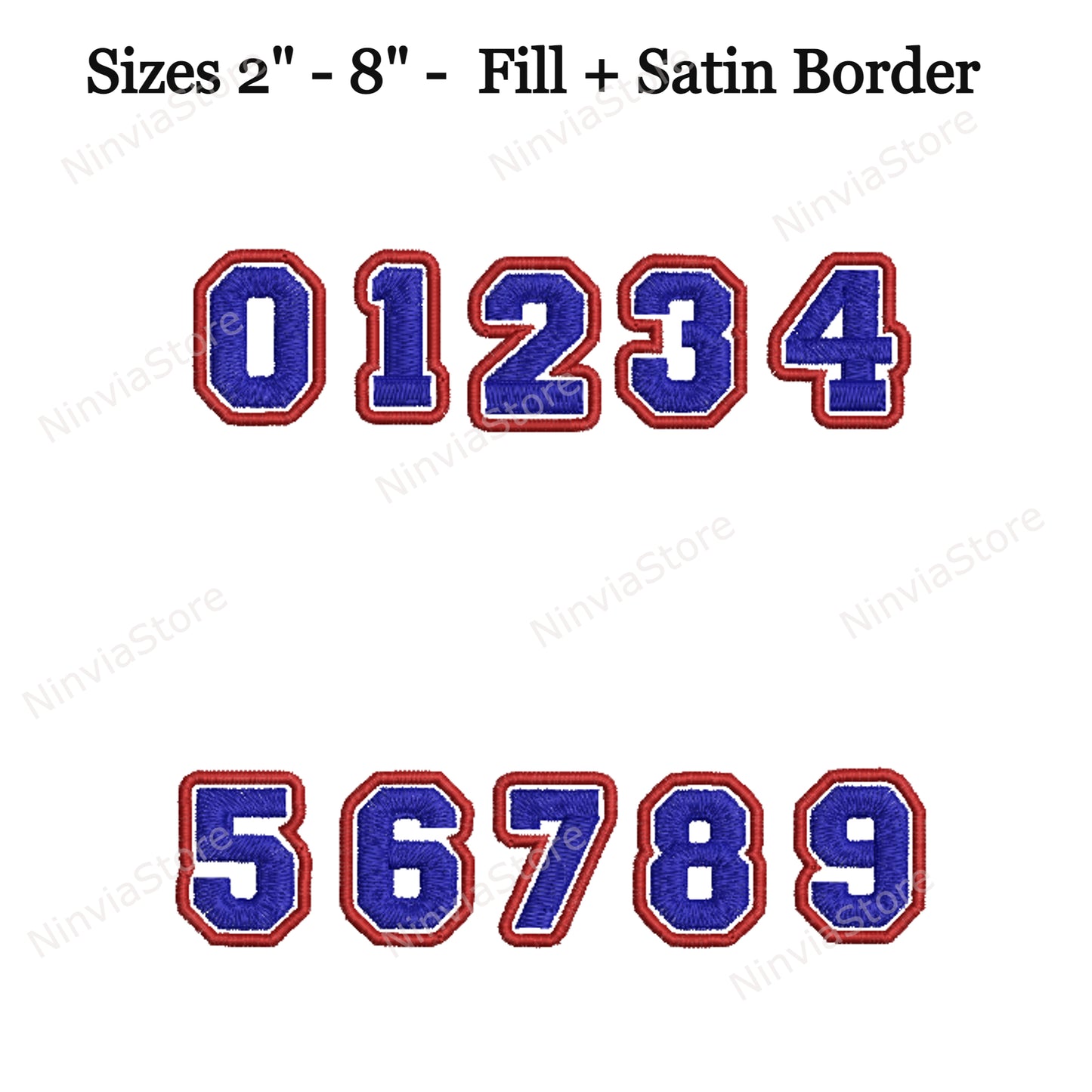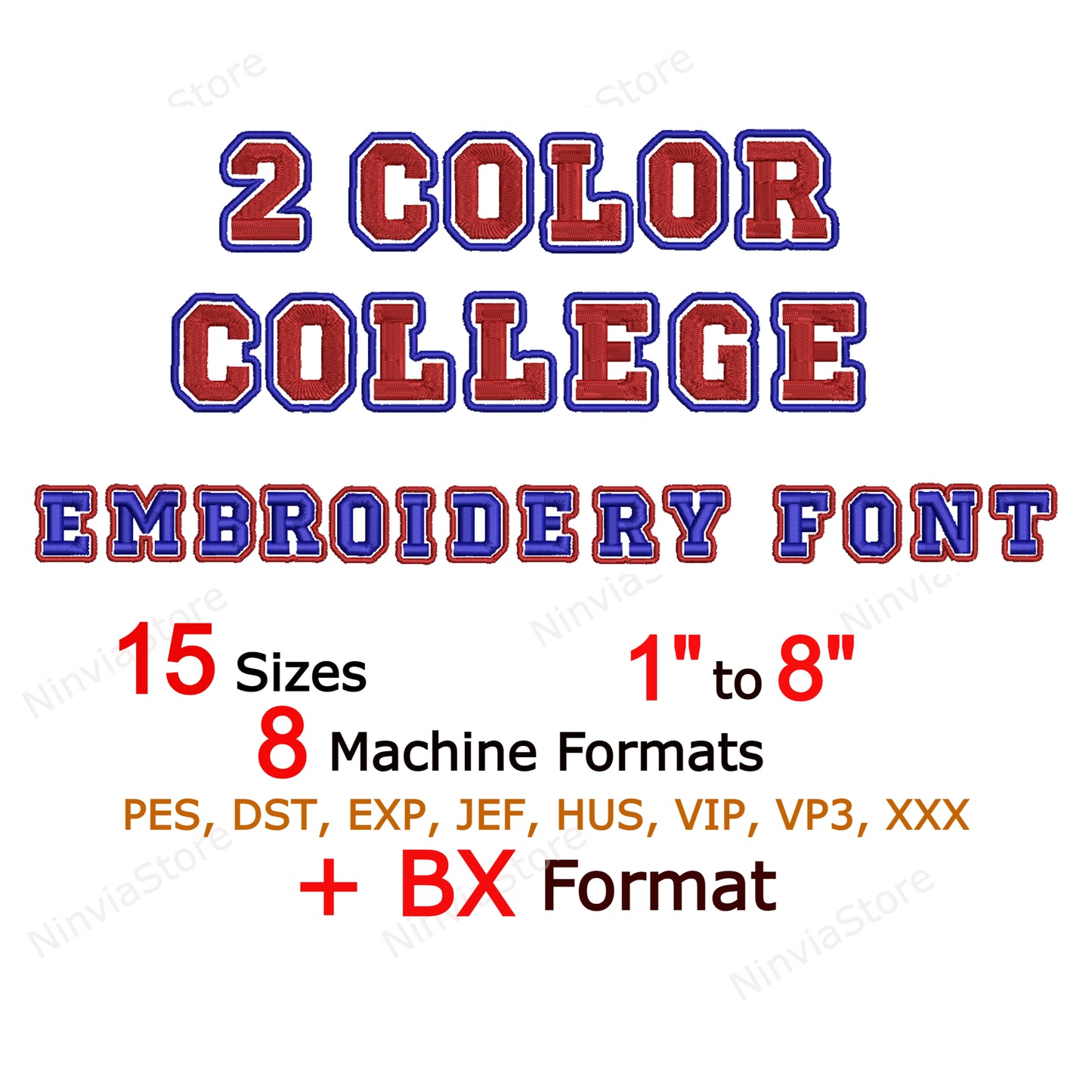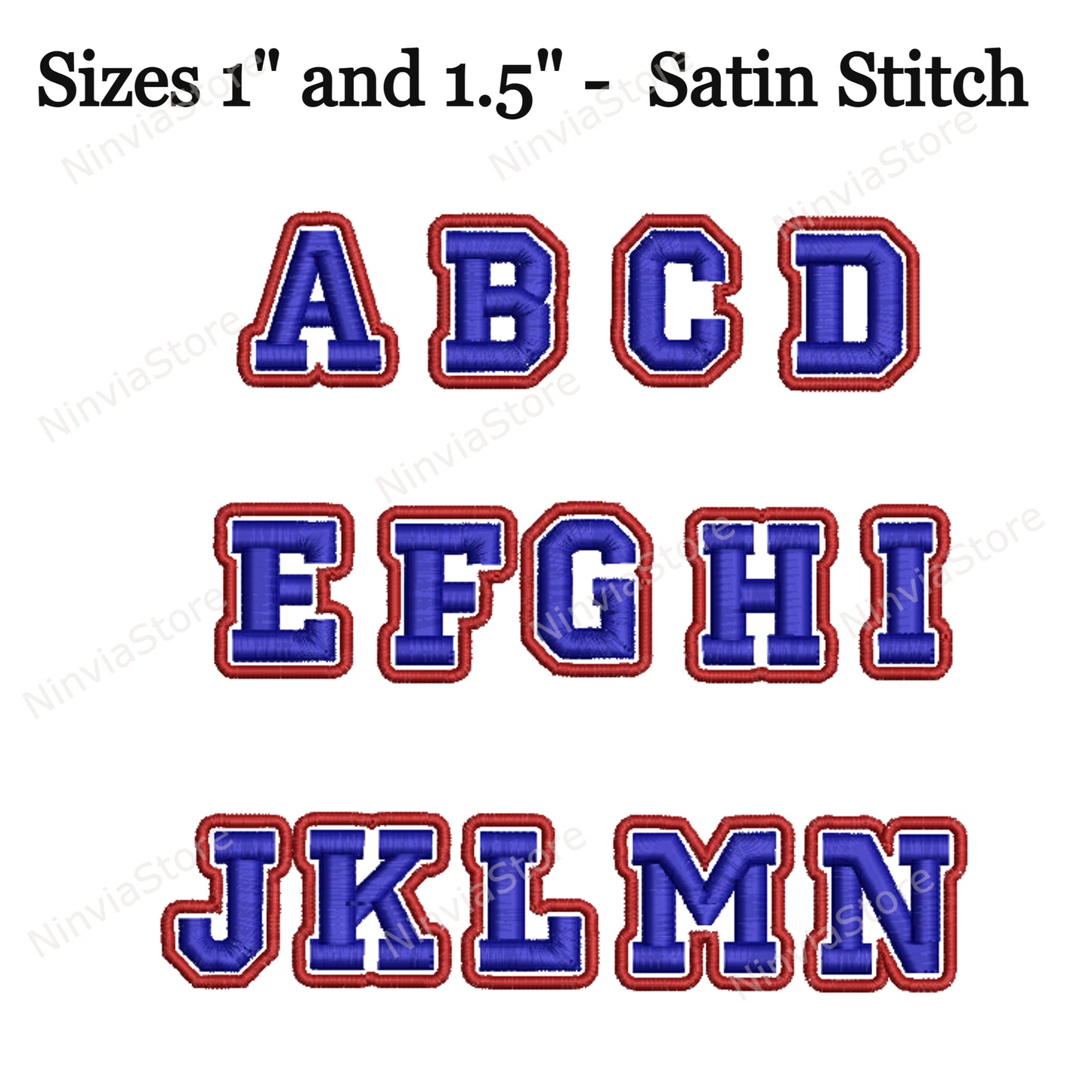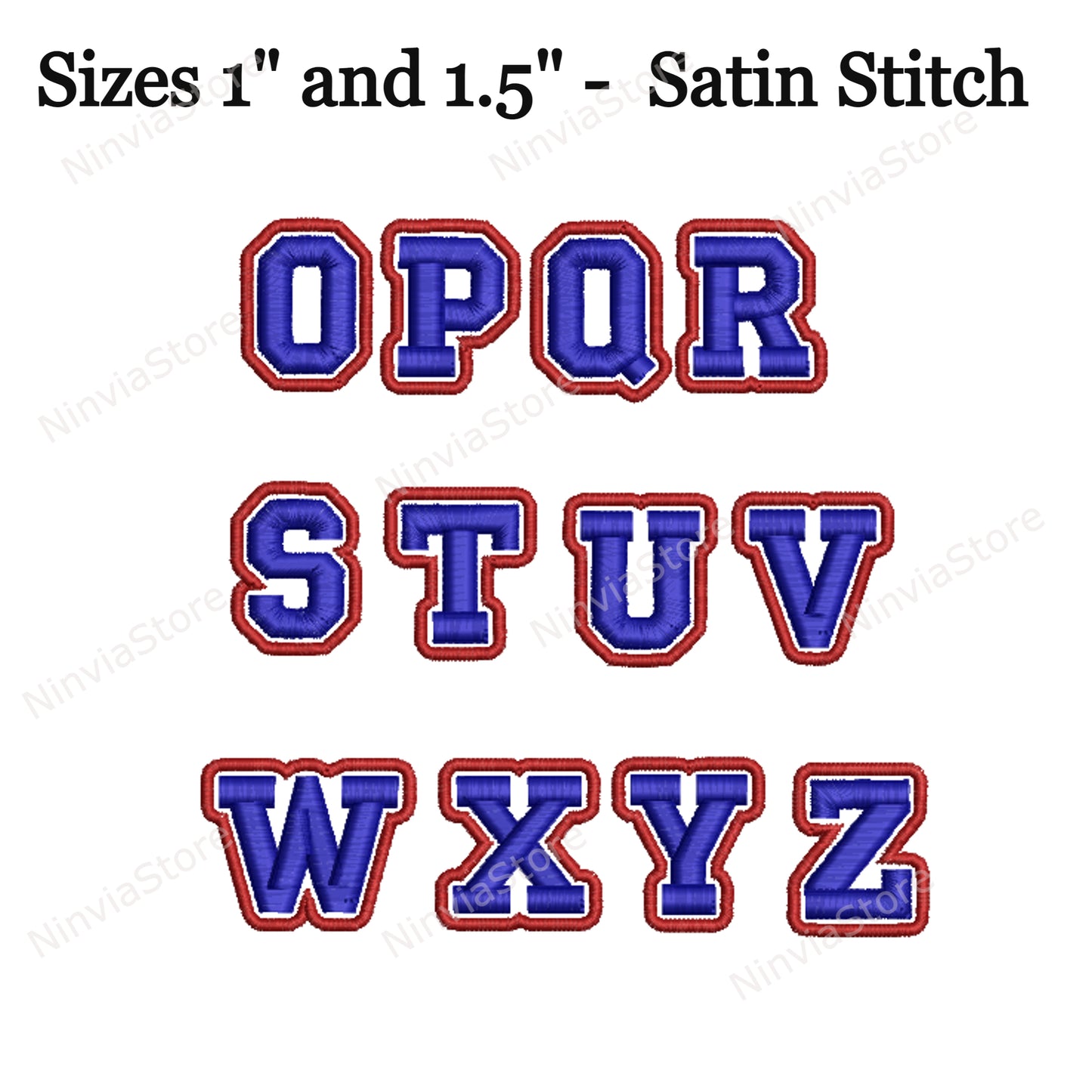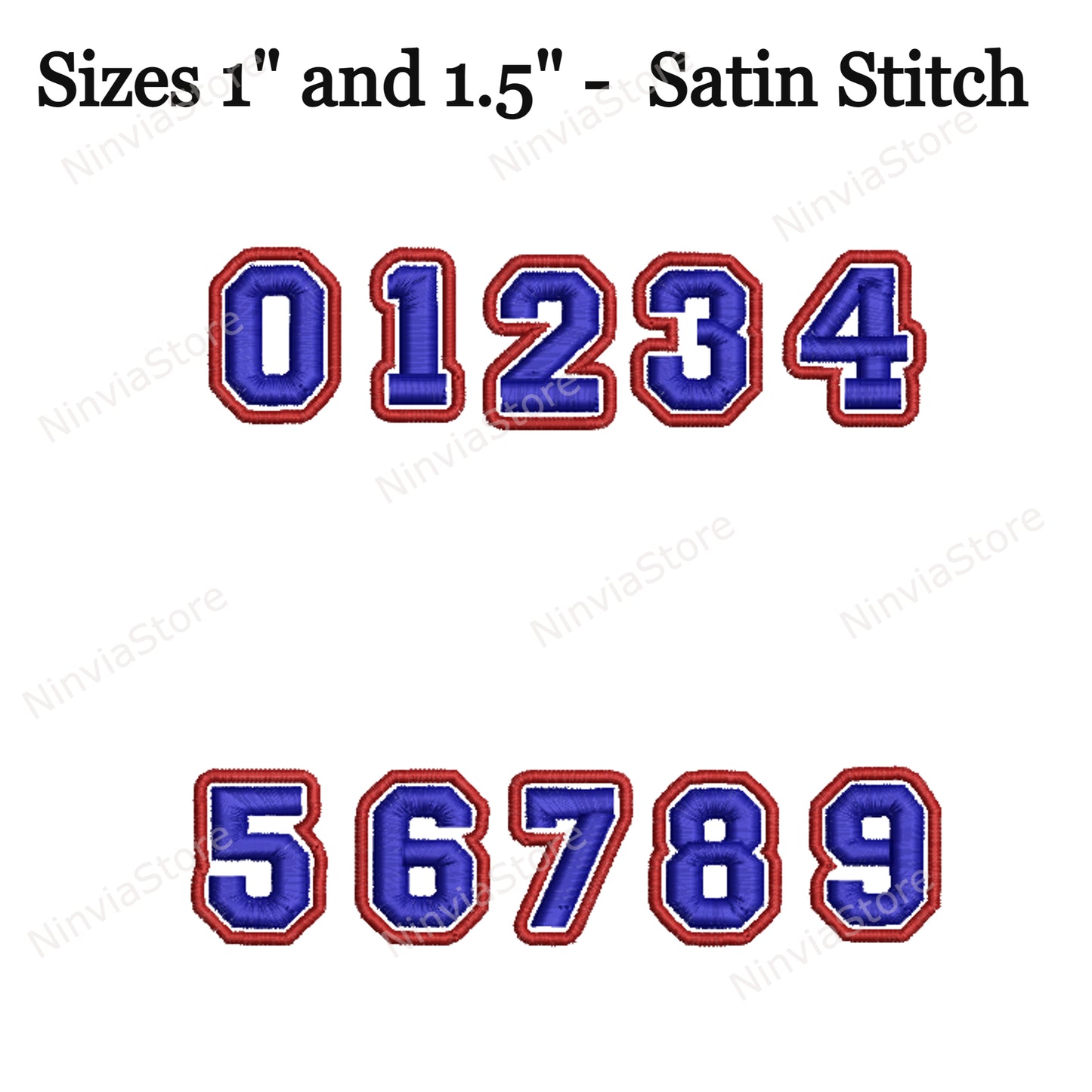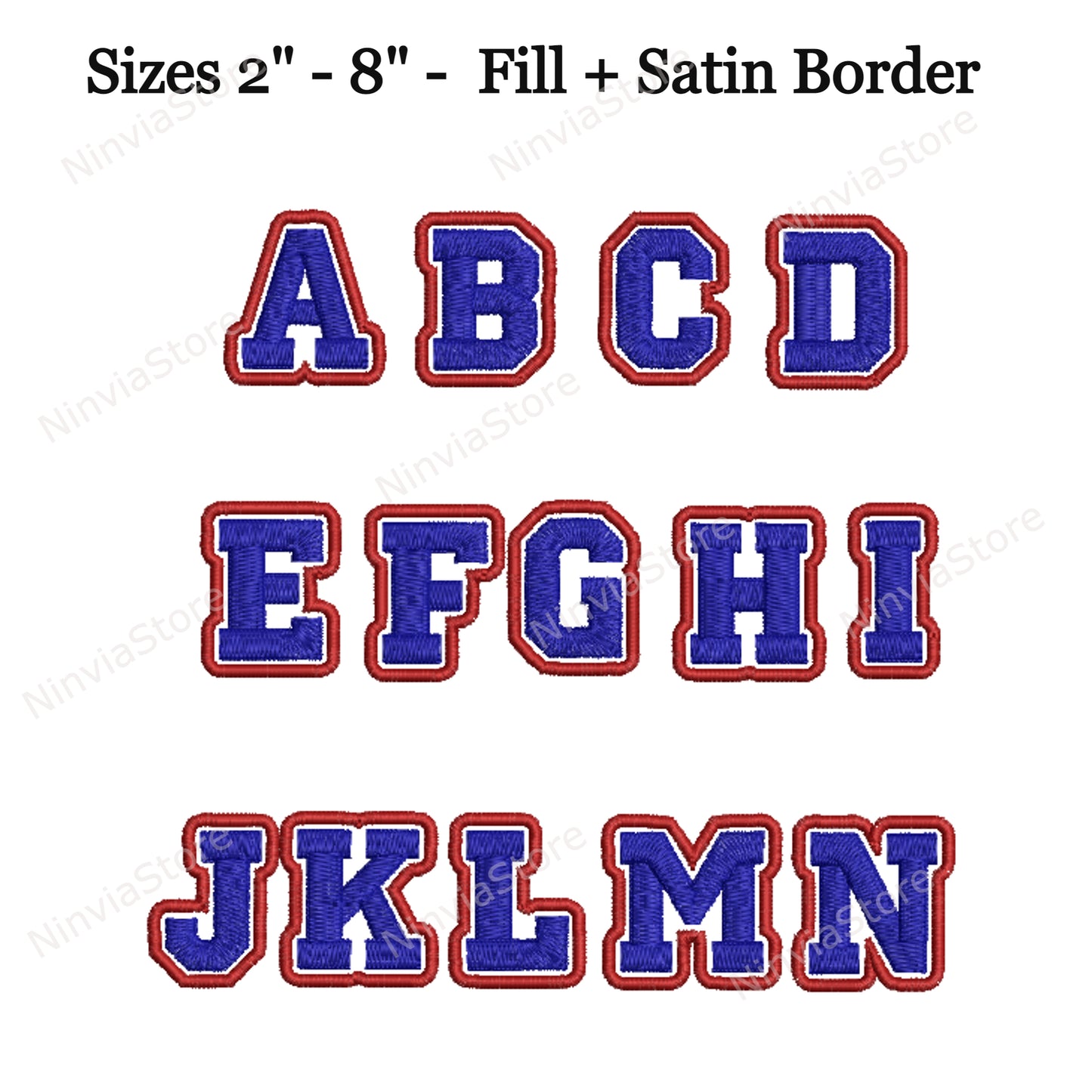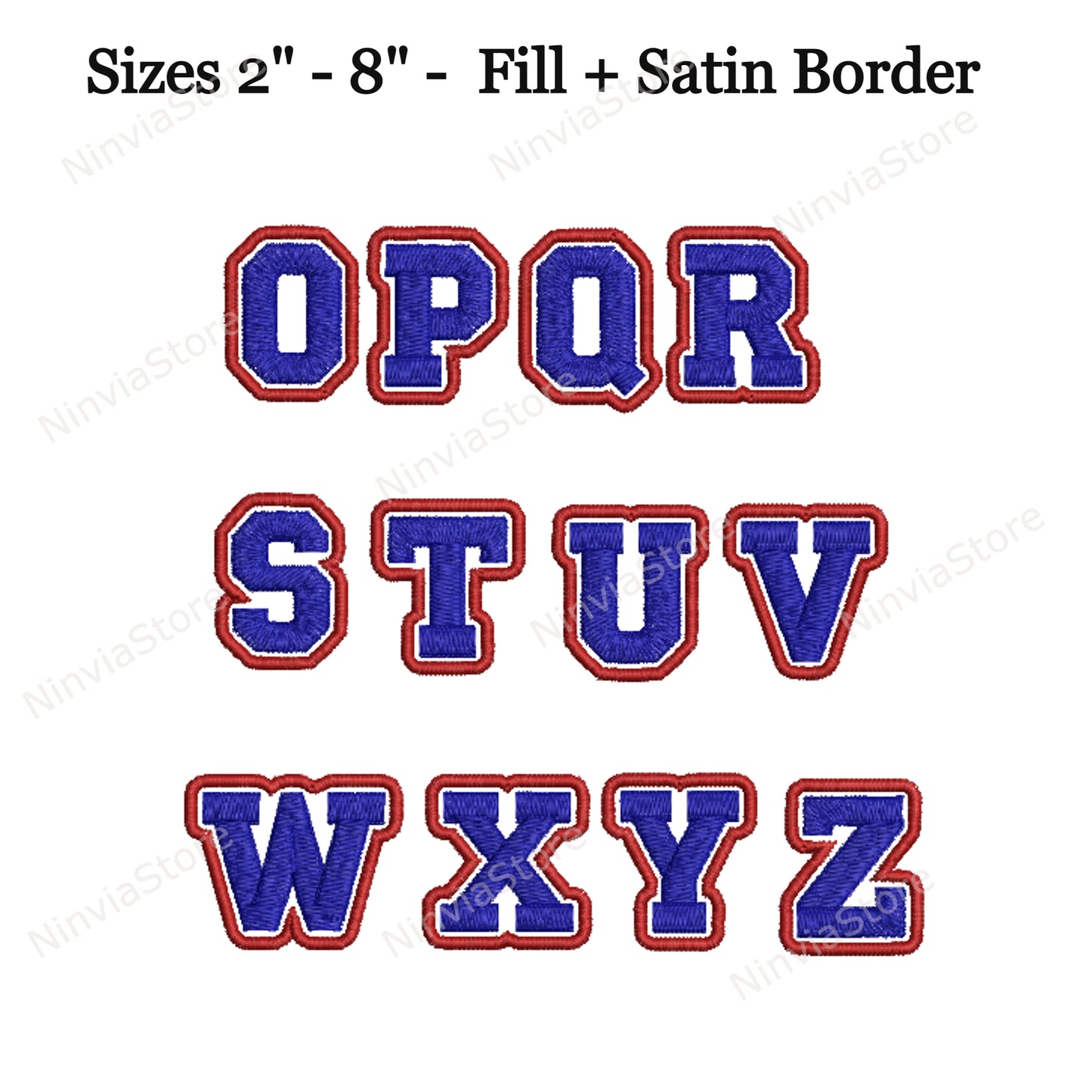
Police de broderie Machine College 2 couleurs, 15 tailles, 8 formats, police Varsity BX, police PE, motifs de broderie Monogram Alphabet
1,5 pouces - Remplissage + Point Satin
2 pouces - Remplissage + Point Satin
2,5 pouces - Remplissage + Point Satin
3 pouces - Remplissage + Point Satin
3,5 pouces - Remplissage + Point Satin
4 pouces - Remplissage + Point Satin
4,5 pouces - Remplissage + Point Satin
5 pouces - Remplissage + Point Satin
5,5 pouces - Remplissage + Point Satin
6 pouces - Remplissage + Point Satin
6,5 pouces - Remplissage + Point Satin
7 pouces - Remplissage + Point Satin
7,5 pouces - Remplissage + Point Satin
8 pouces - Remplissage + Point Satin